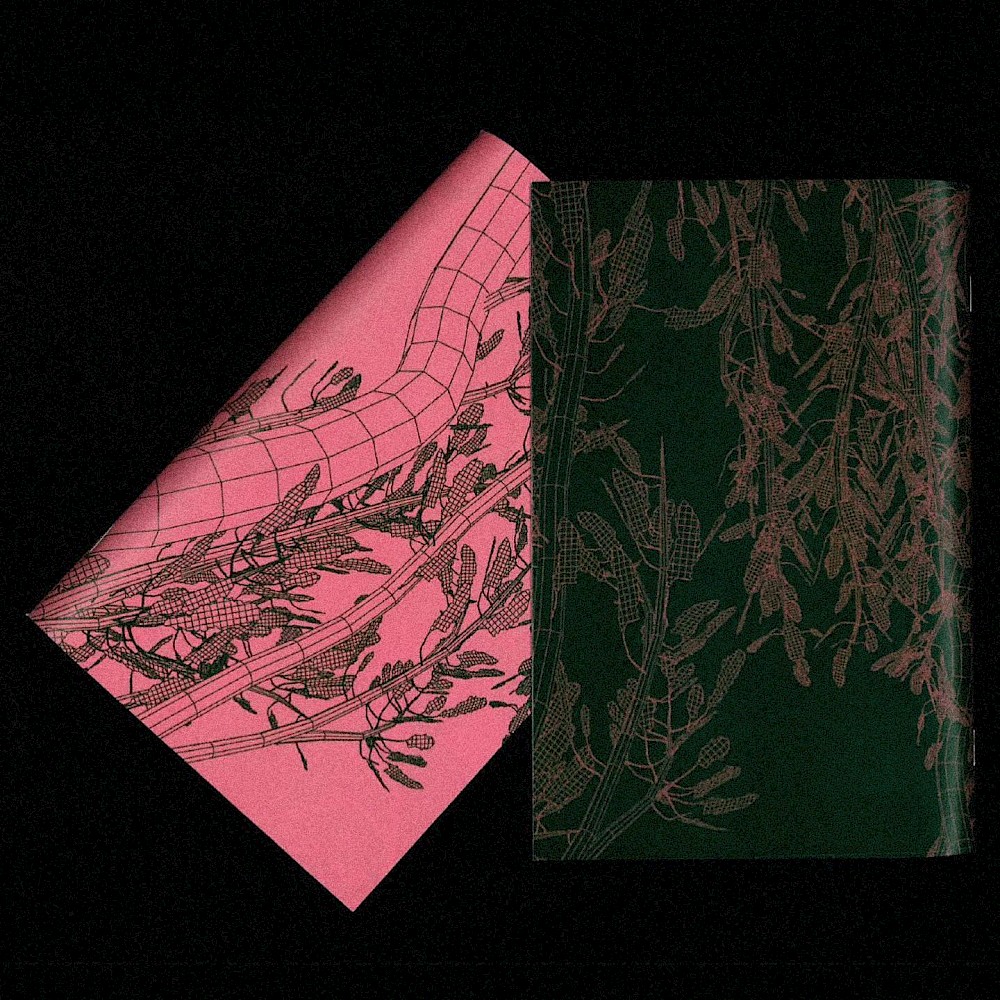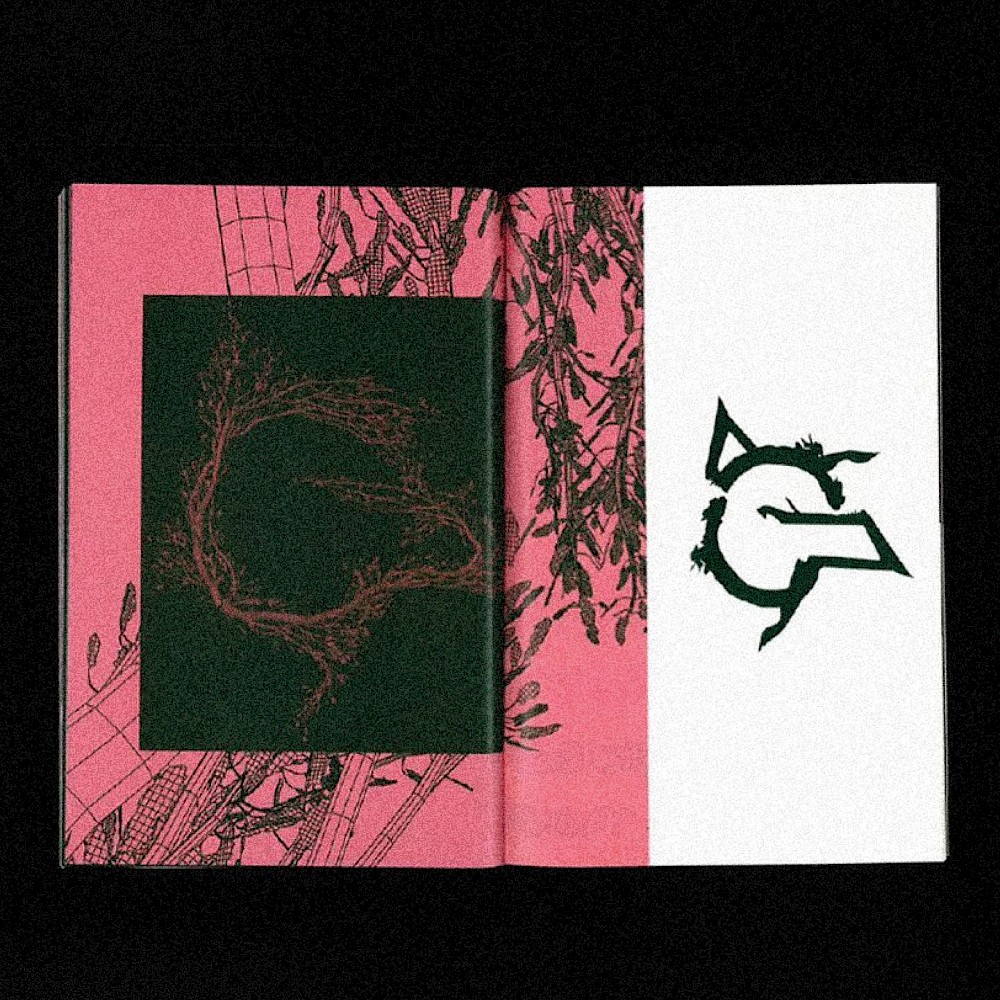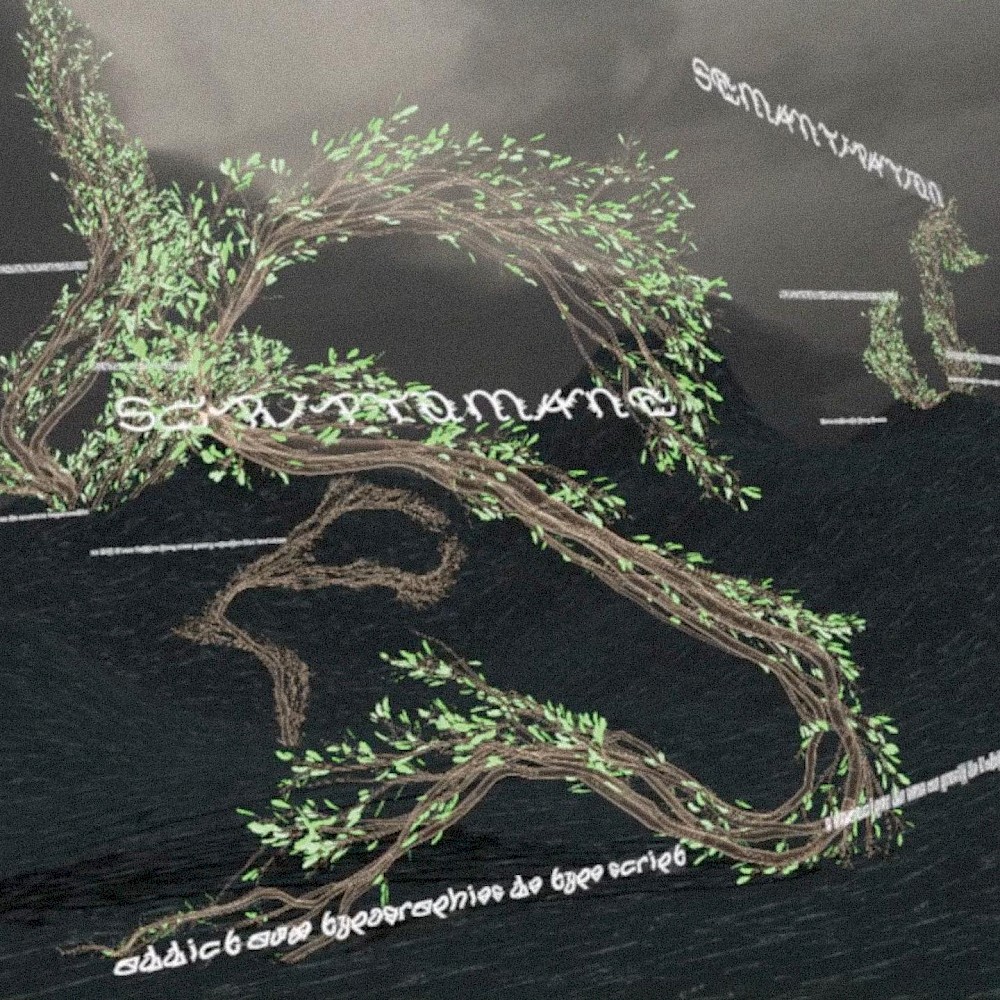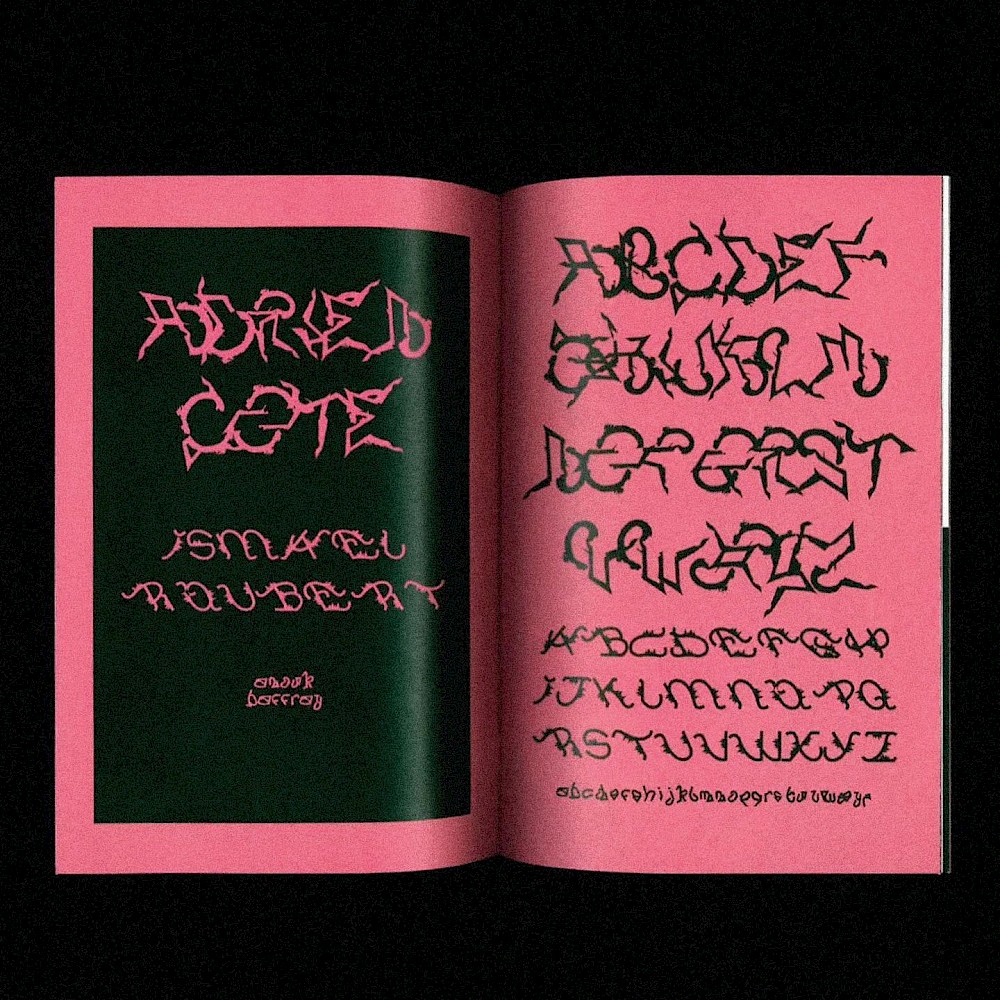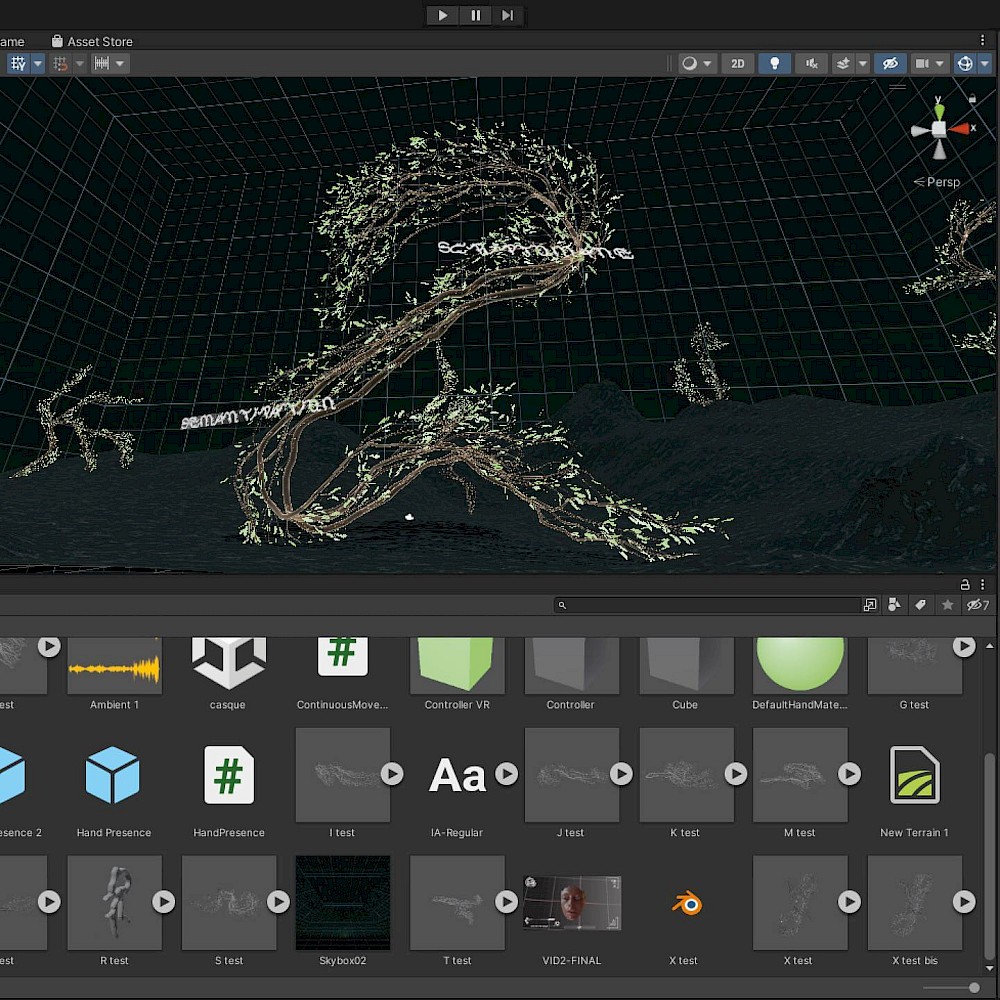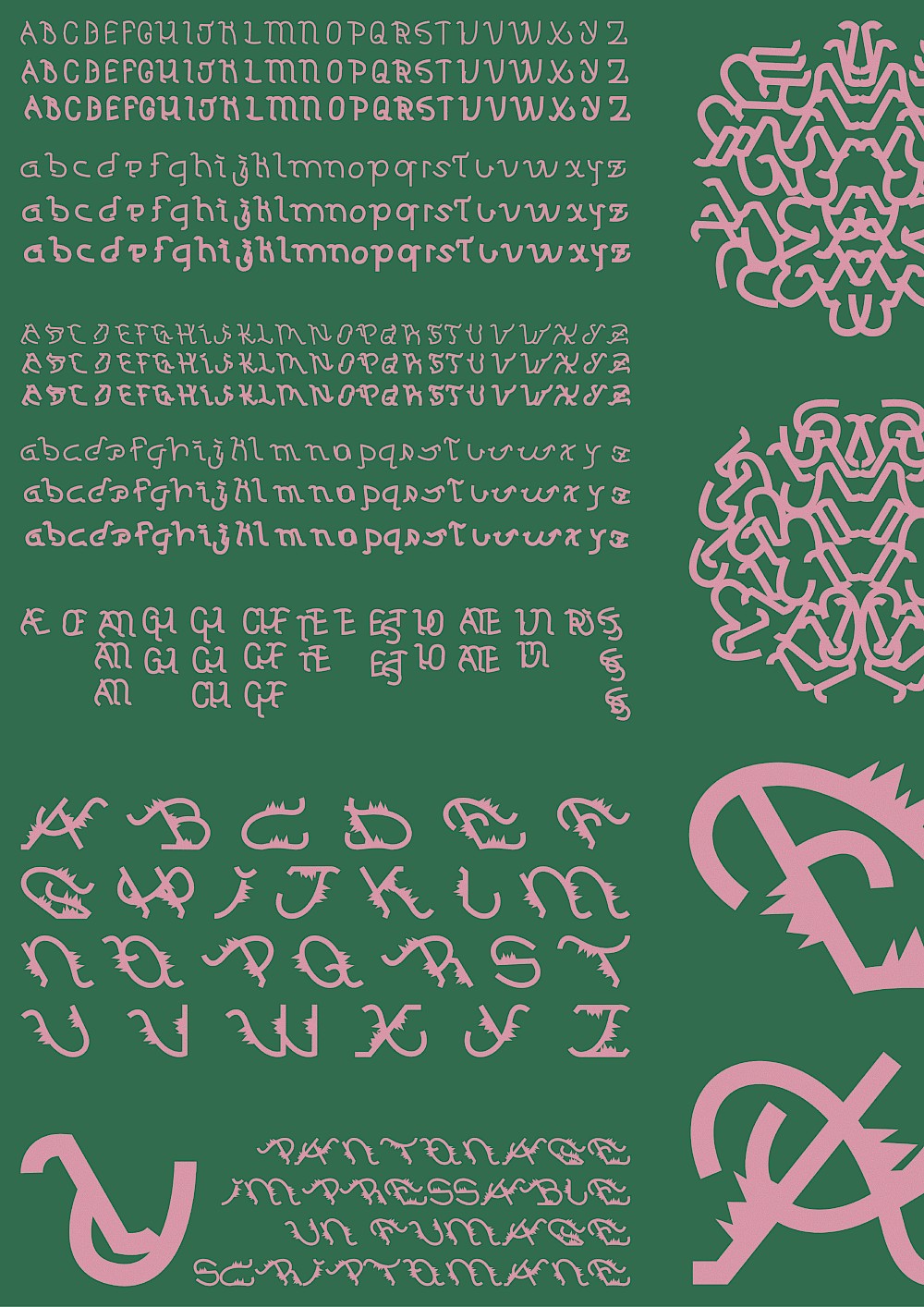
Création d’un ensemble de fonts à partir de modules asémiques, donnant lieu à des dessins de caractères jouant entre la sémantisation via les règles typographiques et l’abstraction des modules. Mise en place du spécimen via la création d’un espace VR ou se mêlent son et exploration. Projet réalisé avec Anouk Baffray et Adrien Côté, à l'Ésad d'Amiens, 2024.
Posters du spécimen typographique. Il y a dessus tous mes tests et différentes graisses qui n'ont pas vu le jour ; libre à vous de les utiliser pour d'autres expérimentations. Le module sur lequel je me suis basé est en bas à gauche sur l'affiche ; vous pouvez, si vous le souhaitez, repartir de celui-ci pour vos dessins de lettres! :)
Création d’un ensemble de fonts à partir de modules asémiques, donnant lieu à des dessins de caractères jouant entre la sémantisation via les règles typographiques et l’abstraction des modules. Mise en place du spécimen via la création d’un espace VR ou se mêlent son et exploration.
Projet réalisé avec Anouk Baffray et Adrien Côté, à l'Ésad d'Amiens, 2024.